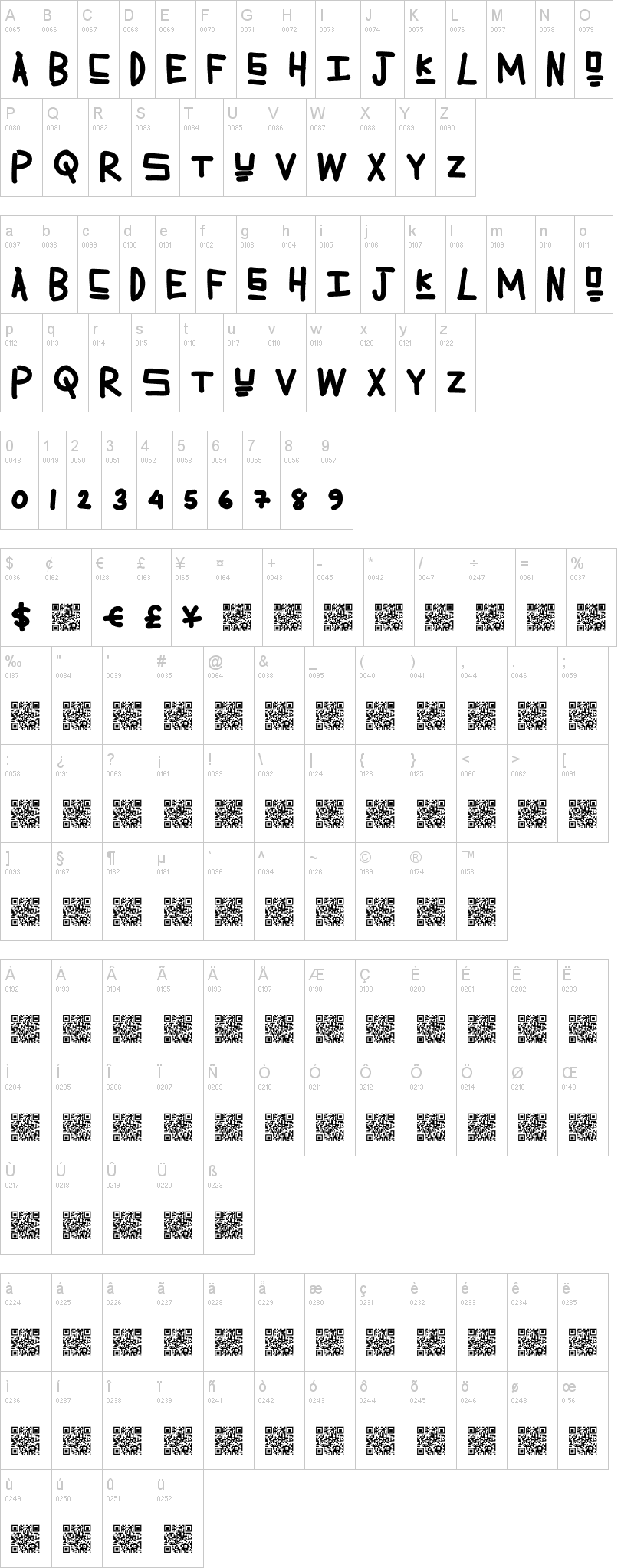
Lemonade Summer是一种轻松、自然、有趣的手写风格字体。它的设计灵感来自于夏天清新的柠檬水,并采用了流畅的线条和有机的形状,以创造出一种温暖、亲切的感觉。这种字体非常适合用于印刷品设计、海报、广告、包装等项目中,可以为您的设计增添一份轻松、有趣的气息。Lemonade Summer 字体包含有小写字母、大写字母、数字和标点符号,同时也支持包括西里尔字母在内的多种语言。内容介绍
Lemonade Summer是一款非常不错的手写艺术字体,具有很好的视觉感,适合于文化类的宣传设计、商业类品牌的广告和产品包装设计以及个性化文字排版等较多场景。